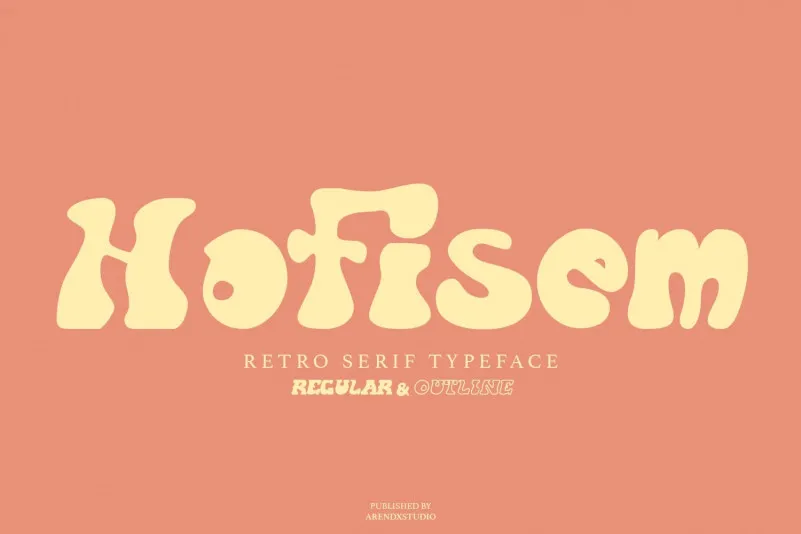
A Hofisem Display Font é uma fonte vintage nos padrões dos anos 70, oferecendo elegância com minimalismo e sofisticação moderna. Suas características são densas e carregadas de personalidade única para cada caractere, o que a torna perfeita para estilos retro ou inspirados neles. Com um traço sólido e robusto, essa fonte apresenta uma grossura perfeitamente adequada aos estilos vintage contemporâneos, proporcionando um look atraente e distinto ideal tanto para criações digitais quanto impressões físicas. Escolha a Hofisem Display Font para adicionar um toque de sofisticação ao seu design gráfico, seja em aplicativos móveis ou impressões de cartazes, garantindo que sua marca seja visível e memorável.